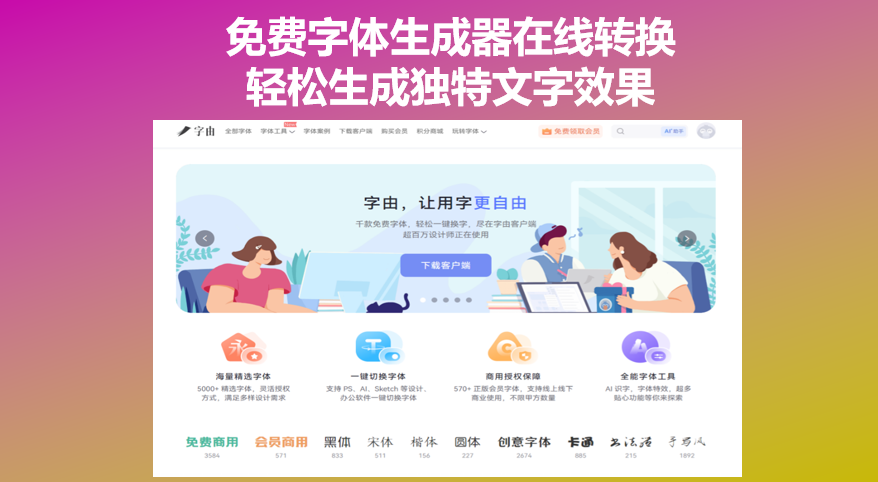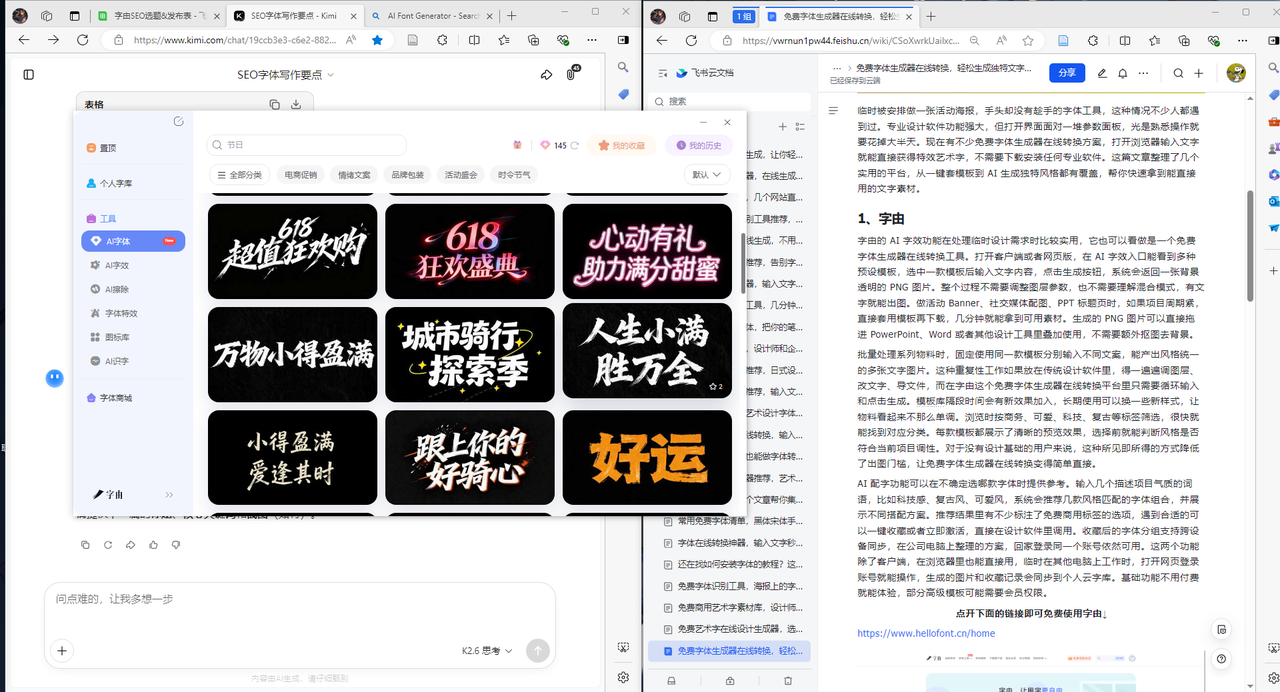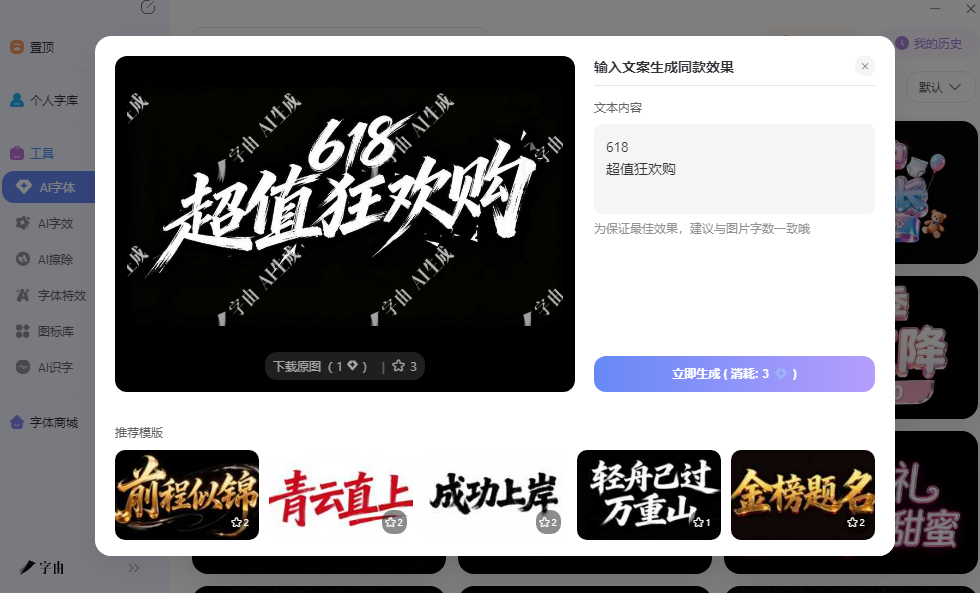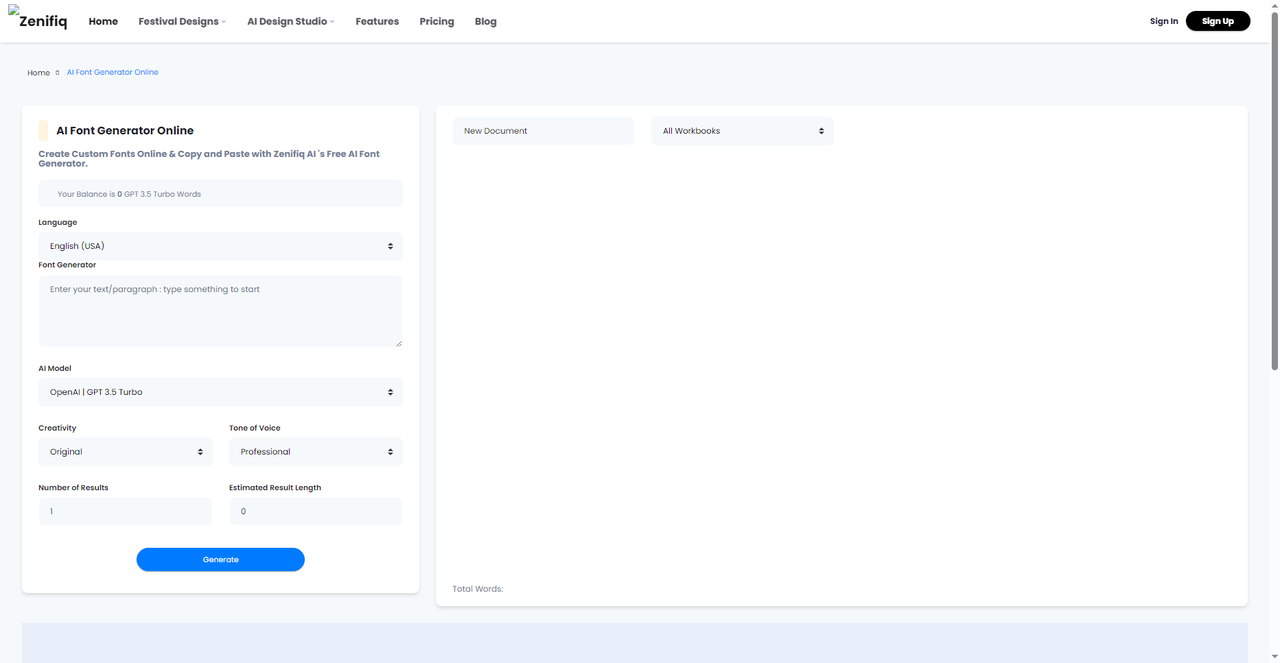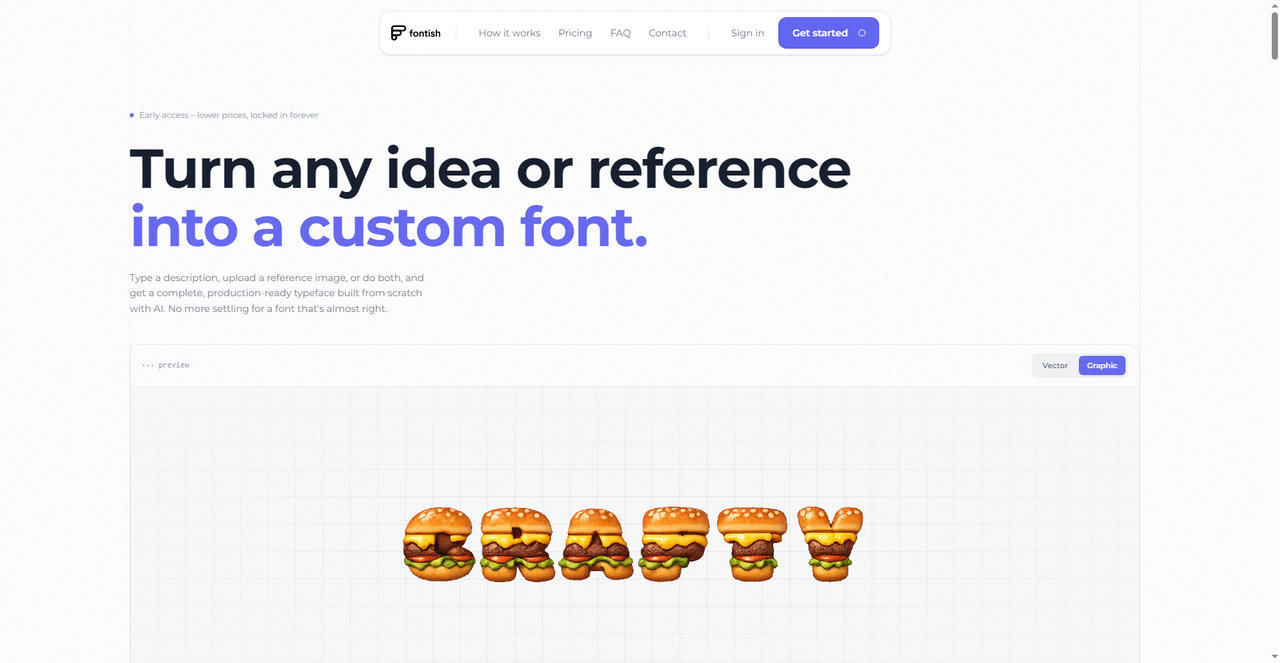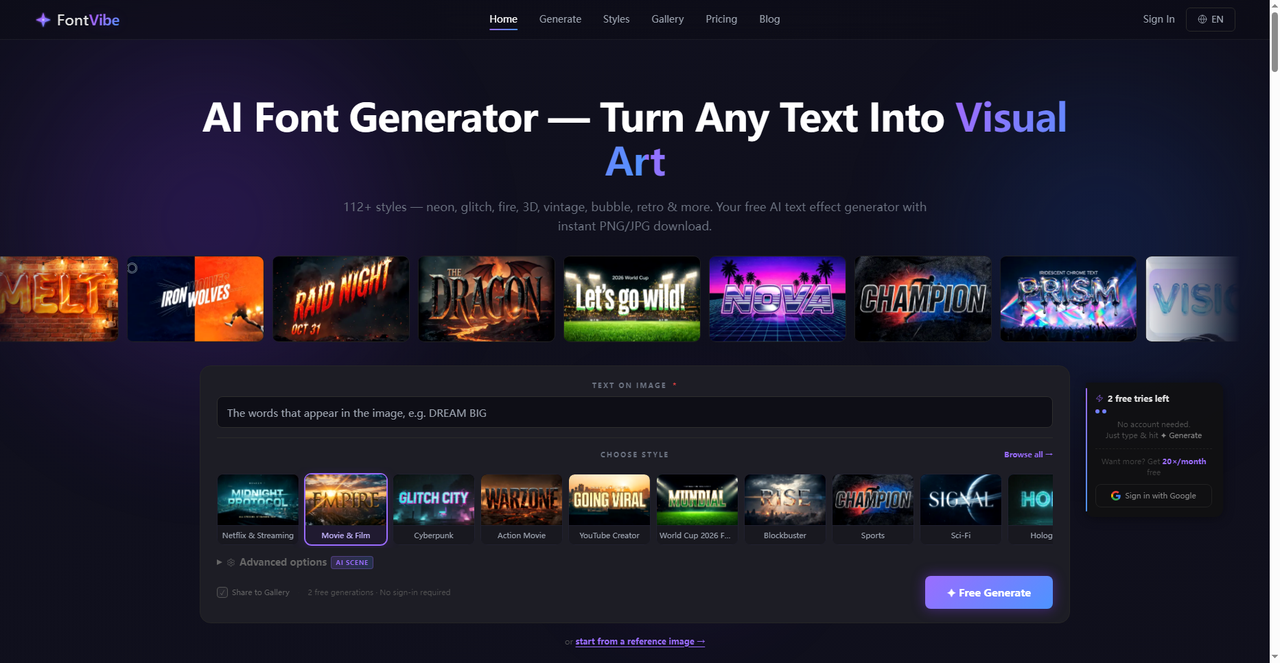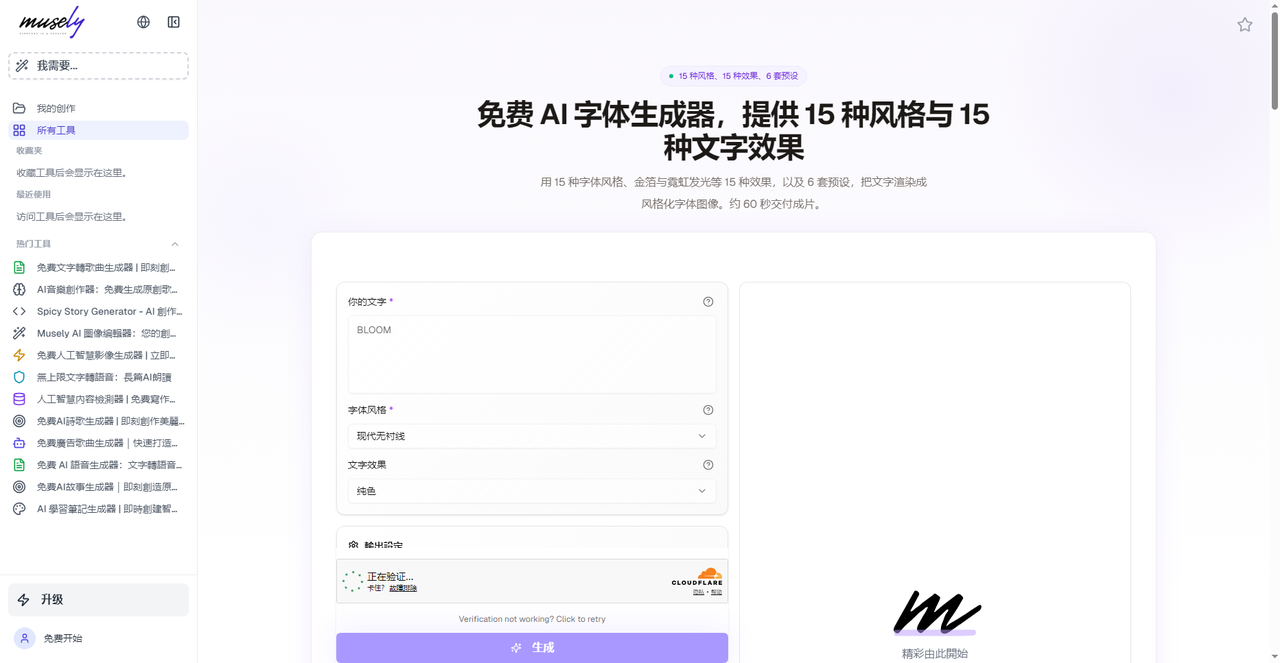
免费字体生成器在线转换,轻松生成独特文字效果
临时被安排做一张活动海报,手头却没有趁手的字体工具,这种情况不少人都遇到过。专业设计软件功能强大,但打开界面面对一堆参数面板,光是熟悉操作就要花掉大半天。现在有不少免费字体生成器在线转换方案,打开浏览器输入文字就能直接获得特效艺术字,不需要下载安装任何专业软件。这篇文章整理了几个实用的平台,从一键套模板到 AI 生成独特风格都有覆盖,帮你快速拿到能直接用的文字素材。
字由的 AI 字效功能在处理临时设计需求时比较实用,它也可以看做是一个免费字体生成器在线转换工具。打开客户端或者网页版,在 AI 字效入口能看到多种预设模板,选中一款模板后输入文字内容,点击生成按钮,系统会返回一张背景透明的 PNG 图片。
整个过程不需要调整图层参数,也不需要理解混合模式,有文字就能出图。做活动 Banner、社交媒体配图、PPT 标题页时,如果项目周期紧,直接套用模板再下载,几分钟就能拿到可用素材。生成的 PNG 图片可以直接拖进 PowerPoint、Word 或者其他设计工具里叠加使用,不需要额外抠图去背景。
批量处理系列物料时,固定使用同一款模板分别输入不同文案,能产出风格统一的多张文字图片。这种重复性工作如果放在传统设计软件里,得一遍遍调图层、改文字、导文件,而在字由这个免费字体生成器在线转换平台里只需要循环输入和点击生成。
Zenifiq 提供了一个 AI Font Generator Online,基于 OpenAI GPT 3.5 Turbo 模型,支持输入文本或段落来生成自定义字体效果。
界面左侧可以调整语言、创意度和语气,语气选项包括 Original 和 Professional,适合不同场景需求。生成前可以预估结果长度,控制输出规模。这个工具的定位偏向文字内容的风格化生成,适合需要批量产出特定语气文案的用户。平台需要注册账号才能使用,生成过程依赖 AI 模型,每次结果会有一定差异。
对于想要尝试 AI 辅助文字创作的人来说,这个工具提供了一种新的工作方式,但生成结果需要人工审核,不适合直接作为最终稿件使用。界面简洁,操作步骤清晰,新手花几分钟就能熟悉整个流程。作为一种免费字体生成器在线转换方案,它更适合探索性创作而非正式交付。
Fontish 的核心能力是帮助用户从零开始创建完整的自定义字体。你可以输入文字描述,或者上传一张参考图片,AI 会根据这些信息生成一套生产就绪的字体文件。输出格式支持 Vector 和 Graphic 两种,矢量格式适合后期编辑和放大使用,图形格式则适合直接导出为图片。这个工具和一般的在线特效生成器不同,它产出的不是单张文字图片,而是一套可以重复使用的字体文件。不过目前平台处于早期访问阶段,部分功能可能需要付费解锁。对于想要拥有独特品牌字体,但又不想支付高昂定制费用的团队来说,Fontish 提供了一条成本较低的途径。生成质量受描述清晰度和参考图质量影响,建议提供明确的风格关键词。注册后可以保存项目进度,方便后续调整优化。这种免费字体生成器在线转换方式适合有明确品牌需求的用户长期投入。
FontVibe 是一个专注视觉特效的 AI 字体生成器,目前提供超过 112 种风格,涵盖霓虹、故障、火焰、3D、复古、气泡等效果。操作方式很直接,在输入框里打字,选择喜欢的风格,点击 Free Generate 就能生成带特效的文字图片。生成结果支持即时下载为 PNG 或 JPG 格式,不需要等待邮件或者跳转其他页面。平台提供 2 次免费生成额度,之后可能需要注册或者付费。风格库更新比较频繁,经常会加入一些时下流行的视觉效果,比如世界杯主题、科幻风格等。对于需要快速获得高冲击力标题文字的用户来说,FontVibe 的模板丰富度和生成速度都比较可观。生成的图片可以直接用于社交媒体封面、视频缩略图或者海报主视觉。下载前可以预览效果,确认满意再保存,避免重复生成浪费额度。这个免费字体生成器在线转换工具在视觉冲击力方面表现突出,适合需要吸睛标题的场景。想要持续使用需要关注免费额度的消耗情况。
Musely 提供了一个免费 AI 字体生成器,支持 15 种字体风格、15 种文字效果和 6 套预设组合。操作流程是输入文字内容,选择字体风格和文字效果,点击生成,大约 60 秒后系统会返回处理完成的图片。平台支持中文输入,对国内用户比较友好。生成前可以调整输出设定,控制最终图片的呈现方式。这个工具的特色在于风格与效果的交叉组合,同一款字体风格搭配不同的文字效果,能产生差异很大的视觉结果,探索空间比较大。对于想要快速尝试多种组合、找到最满意方案的用户来说,这种参数化调整比固定模板更灵活。生成速度受当前服务器负载影响,高峰期可能需要多等一会儿。生成的图片分辨率足够在网页和屏幕展示中使用,但如果是印刷用途,建议确认清晰度是否达标。作为一款免费字体生成器在线转换工具,Musely 在风格组合的多样性上具有一定优势。
总的来说,字由的 AI 字效功能生成背景透明的 PNG 图片,配合收藏分组和跨设备同步,从生成到调用的流程比较完整。其余四款工具的共同点是均聚焦于单一生成或转换功能,无法提供系统级的字体管理和跨软件即时调用能力,且输出的结果多为概念稿、矢量文件或特效图片,适用场景相对有限。可以按具体需求来选择适合自己的免费字体生成器在线转换网站。